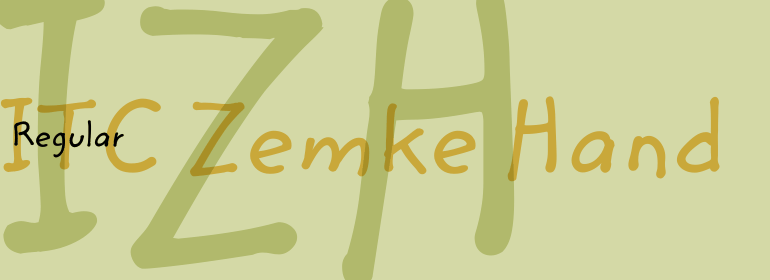
ITC Zemke Hand™
ITC Zemke Hand™,这款字体结构工整、笔画清晰,兼顾美观与易读性,适用于标题、正文、海报、包装、LOGO 等多种场景。字形优雅稳定,风格百搭耐看,适配日常排版与创意设计,让文字呈现更舒适、更具质感。ITC Zemke Hand™一笔一画,皆是细节,以均衡的比例、流畅的线条打造舒适视觉体验,字形端正大气,风格简约现代。无论是商业设计、品牌宣传还是日常排版,都能轻松驾驭,让文字更有格调与力量。ITC Zemke Hand™字体下载。
字体品牌: ITC(Monotype) 设计师:Zemke,Deborah 字体分类:手写风格字体 字体属性:外文 字符集:Unicode 发布时间: 2018